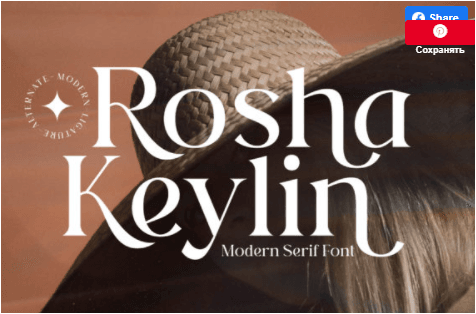
Rosha Keylin Font
Rosha Keylin — стильный и элегантный шрифт с засечками. Он закодирован в PUA, что означает, что вы можете легко получить доступ ко всем глифам и росчеркам! Добавьте его в любой из своих дизайнов и наслаждайтесь результатами!